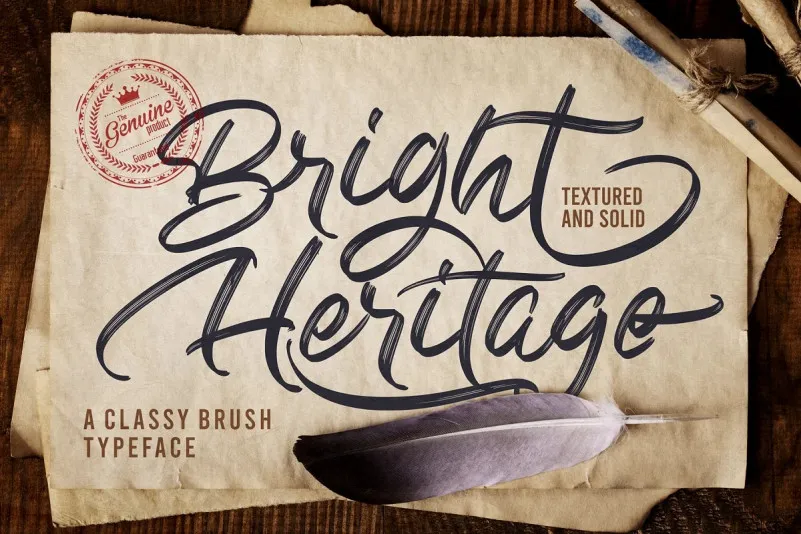
Bright Heritage Font – Download Grátis
A Bright Heritage Font é uma escolha perfeita para quem busca trazer vida e unidade a suas criações digitais. Desenvolvida com extrema atenção aos detalhes do pincel, esta fonte script proporciona um estilo sofisticado que garantirá uma pegada impactante em seus logos, imagens de marca, citações escritas a mão, embalagens de produtos, materiais de merchandising, postagens nas redes sociais e até mesmo páginas web. Perfeita para quem valoriza tanto a elegância quanto a autenticidade, a Bright Heritage é uma fonte script que eleva qualquer projeto digital ao próximo nível, tornando-o ainda mais chamativo e memorável.